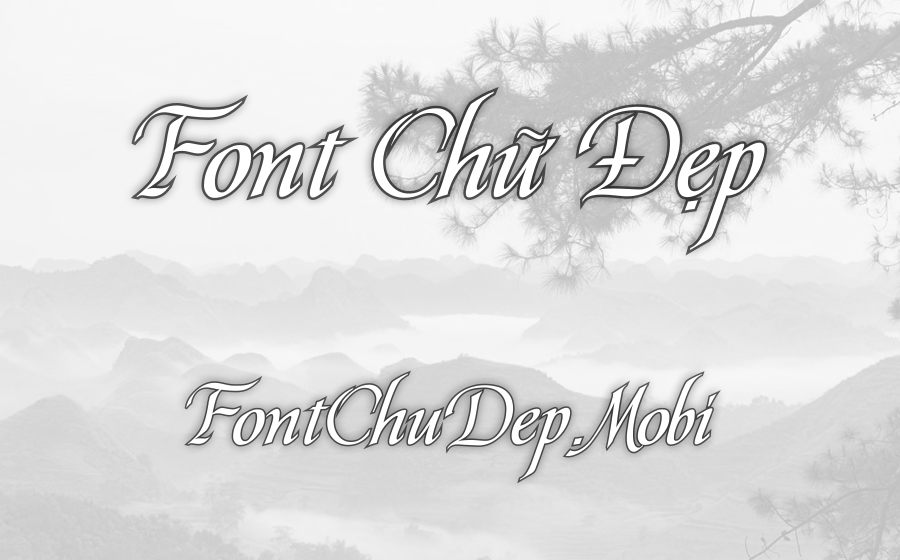
Font UTM Pierre Việt Hóa
UTM Pierre
UTM Pierre là một font chữ serif mà mình cực kỳ ấn tượng, không chỉ bởi vẻ đẹp cổ điển và sang trọng mà nó mang lại, mà còn bởi sự thanh lịch và chuyên nghiệp trong từng chi tiết thiết kế. Với các đường nét tinh tế, độ tương phản cao cùng chân chữ rõ ràng, UTM Pierre thực sự làm tăng khả năng đọc một cách tuyệt vời, đồng thời cuốn hút ánh nhìn ngay từ cái nhìn đầu tiên. Đặc biệt, font này đã được Việt hóa hoàn hảo để hỗ trợ tiếng Việt, mở rộng khả năng áp dụng vào nhiều lĩnh vực thiết kế khác nhau. Mình thật sự đánh giá cao sự tâm huyết của đội ngũ tại FontChuDep.mobi khi đã sưu tầm và giới thiệu font chữ độc đáo này, giúp các nhà thiết kế có thêm nguồn tài nguyên chất lượng để áp dụng vào các dự án thực tế.
Không những vậy, UTM Pierre còn rất linh hoạt trong việc ứng dụng thực tế. Phong cách cổ điển và tinh tế của nó rất phù hợp với các dự án như thiết kế logo, tiêu đề, bao bì sản phẩm, hay các ấn phẩm in ấn và nội dung thương hiệu. Mình đặc biệt thấy rằng, trong các lĩnh vực như quảng cáo, giáo dục, thiệp cưới và công nghệ, việc sử dụng font chữ này sẽ góp phần tạo nên sự sang trọng và chuyên nghiệp, giúp các sản phẩm thiết kế nổi bật và để lại ấn tượng sâu sắc trong lòng người sử dụng. Thật sự là một trải nghiệm không thể bỏ qua cho các nhà thiết kế đang tìm kiếm sự mới mẻ và độc đáo!